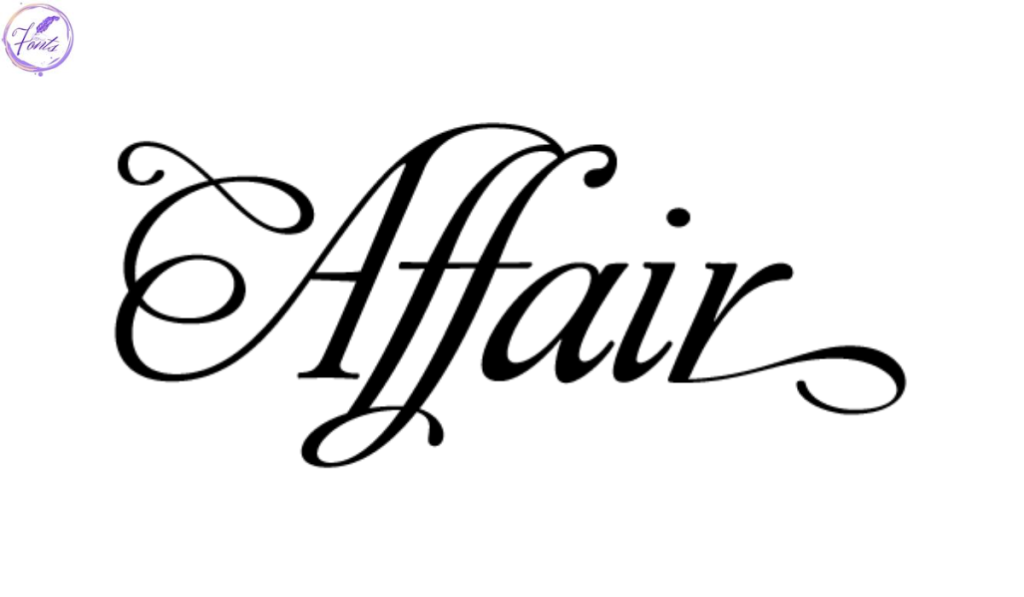
Affair font việt hóa
Tác giả: Alejandro Paul
Ngày phát hành: 2006
Ngôn ngữ: Tiếng Việt và một số ngôn ngữ khác
Bộ Font: Affair
Phân loại: Cá tính, Độc đáo, Cổ điển, Hiện đại
Kiểu chữ: Kiểu chữ viết tay (script)
Affair font là một bộ font sang trọng, mang đậm phong cách cổ điển và quý phái. Được thiết kế bởi nhà thiết kế tài năng Alejandro Paul vào năm 2006, affair font nhanh chóng trở thành một lựa chọn phổ biến cho các dự án cần sự tinh tế và đẳng cấp. Với các đường nét mượt mà và chi tiết tỉ mỉ, affair font phù hợp cho nhiều mục đích sử dụng như thiệp mời, thiết kế logo, và các sản phẩm truyền thông cao cấp. Phiên bản Việt hóa của affair font giúp người dùng dễ dàng sử dụng trong các văn bản tiếng Việt, tạo nên những sản phẩm thiết kế đẹp mắt và ấn tượng.
Đánh giá affair font
Affair font nhận được nhiều lời khen ngợi từ cộng đồng thiết kế nhờ vào vẻ đẹp cổ điển và sự tinh tế của nó. Các nhà thiết kế đánh giá cao affair font bởi sự thanh lịch và dễ đọc, giúp truyền tải thông điệp một cách hiệu quả và nổi bật. Font này đặc biệt phù hợp cho các dự án cần sự sang trọng và chuyên nghiệp, từ thiệp cưới, bìa sách đến các sản phẩm quảng cáo cao cấp. Phiên bản Việt hóa của affair font không chỉ giữ nguyên được phong cách độc đáo của bản gốc mà còn bổ sung đầy đủ các ký tự tiếng Việt, đáp ứng mọi nhu cầu sử dụng của người dùng.